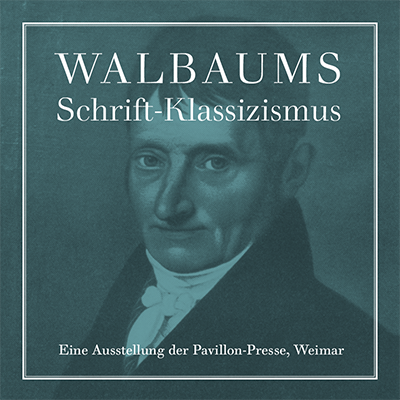
Auf Bitten von Friedrich Justin Bertuch verlegt der Schriftschneider Justus Erich Walbaum 1803 seine Schriftgießerei von Goslar nach Weimar. Hier, im Zentrum der Deutschen Klassik, schuf Walbaum ein umfangreiches und vielgelobtes Werk von Schriftarten verschiedenster Gattungen.
Aus heutiger Sicht als herausragend betrachtet wird dabei vor allem seine Walbaum Antiqua. Sie gilt heute als einer der bedeutendsten deutschen Beiträge zur Gattung der klassizistischen Schriften und wird nach wie vor gern und oft verwendet. Und dies, obwohl sie zur Zeit ihrer Entstehung nur selten in Anwendung war. Denn trotz der Bemühungen namhafter Verleger zur Durchsetzung der Antiqua-Schrift, gestaltete sich der Druck der feingliedrigen klassizistischen Schriften zu dieser Zeit als schwierig und das deutschsprachige Publikum bleibt größtenteils der Fraktur verhaftet. Im 20. Jahrhundert wird die Walbaum Antiqua jedoch wiederentdeckt und erlebt eine Renaissance.
Die Ausstellung »Walbaums Schriftklassizismus« beleuchtet die Geschichte der Walbaum Antiqua und verwandter klassizistischer Schriften unter besonderer Berücksichtigung des Antiqua-Fraktur-Streites im deutschen Sprachraum zur Zeit der Klassik.